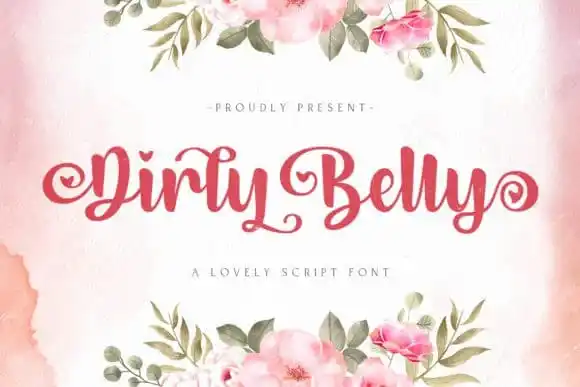
Dirly Belly Script Font – Download Grátis
A Dirly Belly Script Font é uma nova elegante tipografia script que traz à tona a beleza do estilo livre. Este tipo de fonte é perfeitamente adequada para designs de marca, projetos de menu e embalagens de produtos, bem como para qualquer projeto que necessite da aplicação de texto com destaque em um fundo de imagem. Desenvolvida pela Font Designer StringLabs, a Dirly Belly Script mantém sua influência clássica do calligrafista enquanto permanece atual e fresca. Seja você designer ou artista gráfico, esse tipo de fonte é o que você precisa para trazer seus projetos para um nível superior. Engane-se com essa bela tipografia script e veja suas criações florescer em design criativo e elegante.